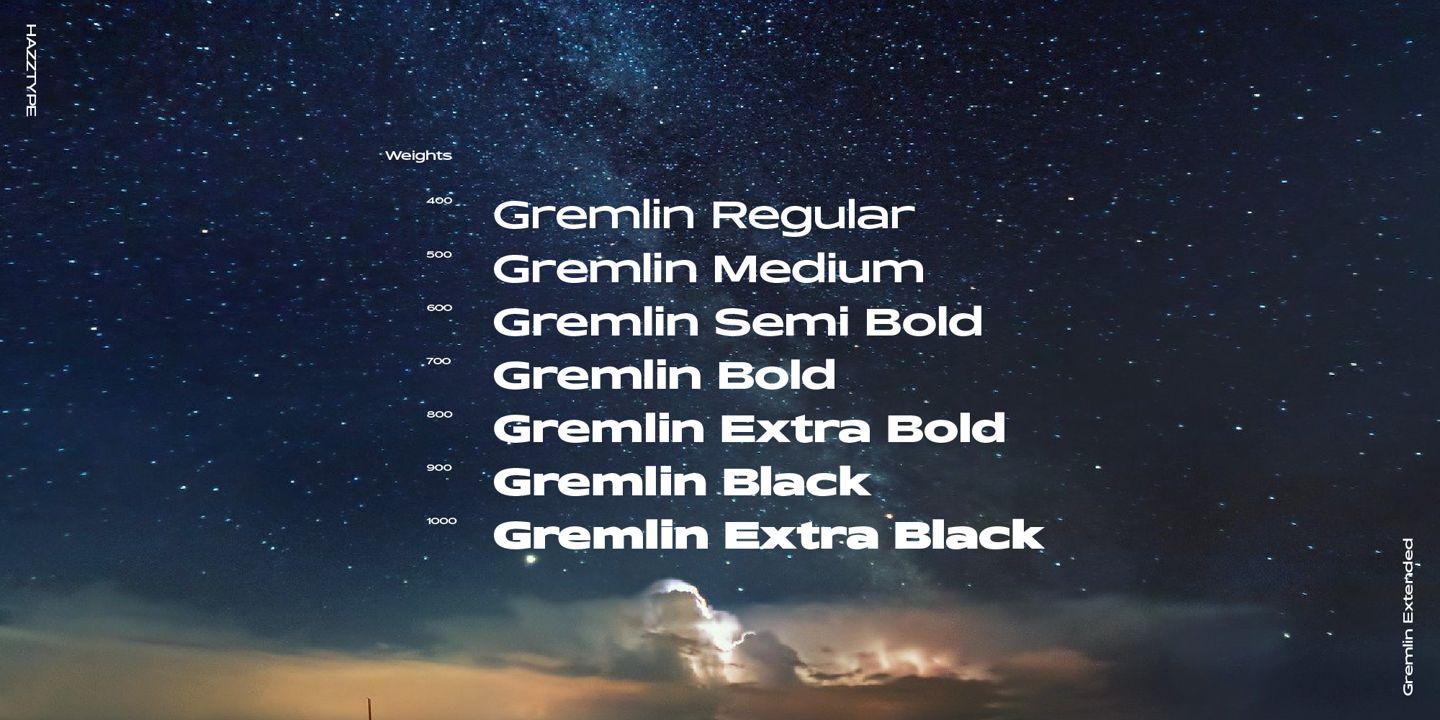
Gremlin Font Family
Description de Gremlin Font Family
Gremlin est une police sans empattement à largeur étendue. La famille comprend 6 polices dans une variété de graisses et plus de 300 glyphes alternatifs. La police prend également en charge un grand nombre de langues latines et cyrilliques. Cette police confiante peut être utilisée à diverses fins, telles que le texte, les logos, les titres et l’image de marque.